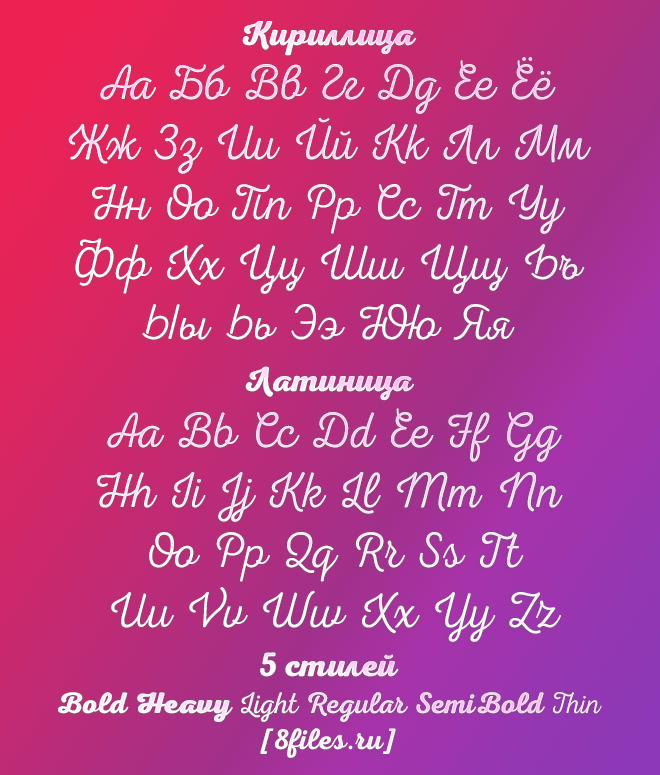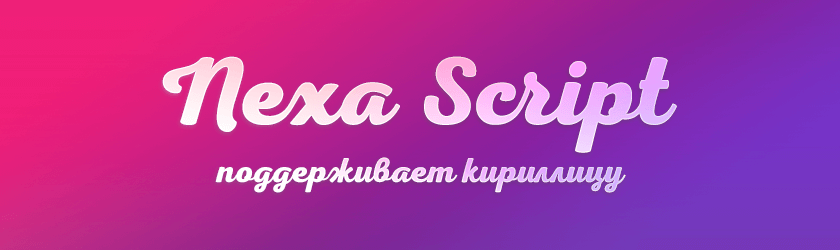
Font (шрифт) Nexa Script
Представляю вашему вниманию крутой и современный шрифт Nexa Script. В него входит 5 стилей, а так же шрифт поддерживает Кириллицу. Забирай себе друг